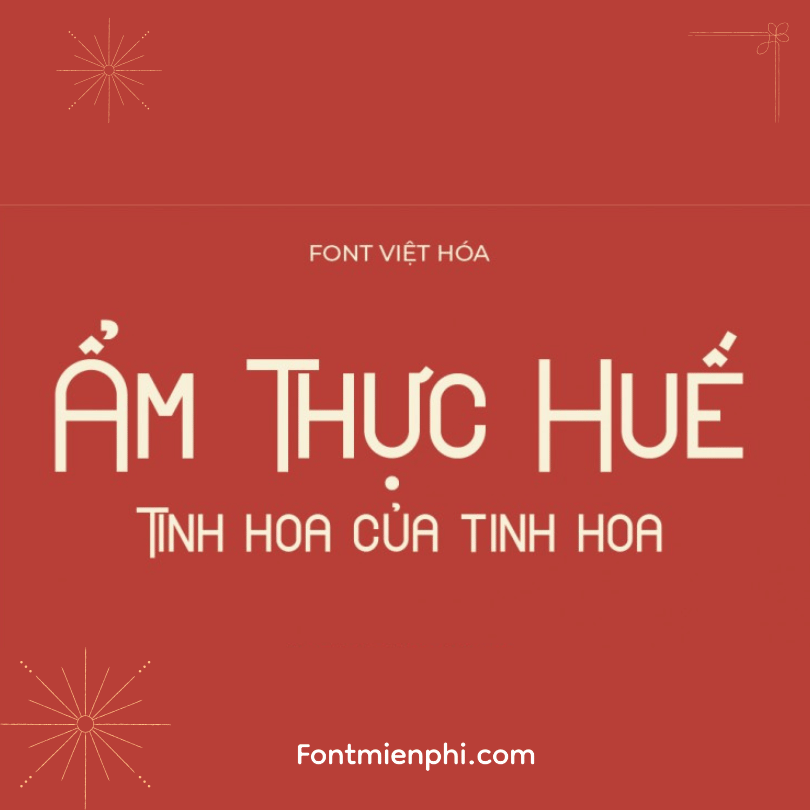
Font việt hoá VL Cvetanoff
Font việt hoá VL Cvetanoff – Phong Cách Handwritten Đầy Cảm Xúc
Font VL Cvetanoff đã được Việt hóa hoàn chỉnh, mang đến nét chữ viết tay (handwritten) mềm mại, lãng mạn và đầy cảm xúc. Với những đường nét tự nhiên như được viết bằng bút lông, font chữ này là lựa chọn hoàn hảo cho:
ỨNG DỤNG NỔI BẬT:
✔ Thiết kế thiệp mời, thiệp cưới
✔ Logo thương hiệu thời trang, mỹ phẩm
✔ Bao bì sản phẩm cao cấp
✔ Poster nghệ thuật, quote truyền cảm hứng
ĐẶC ĐIỂM NỔI BẬT:
✓ Hỗ trợ đầy đủ bộ dấu tiếng Việt
✓ Nét chữ mềm mại, thanh thoát tự nhiên
✓ Đa dạng kiểu chữ (Regular, Bold, Italic)